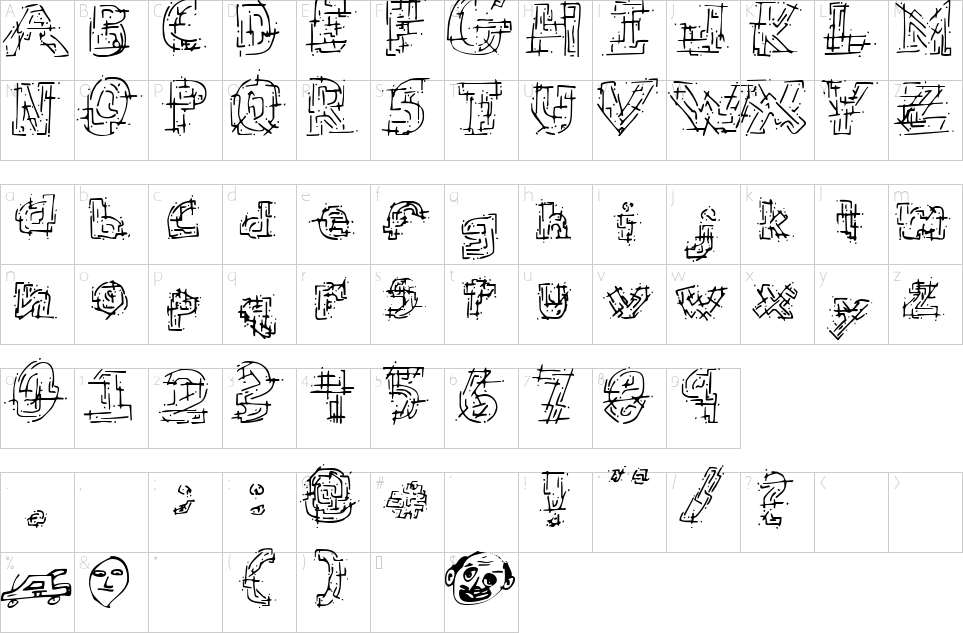
A fonte Chaotic Circuit é um adereço perfeito para quem busca algo que destaque seu design no meio vibrante e inovador do digital. Desenvolvida por Bionic Type, essa fonte criativa ganhou a confiança de muitos criadores ao longo de suas downloads. Com uma aparência que parece ser um circuito elétrico mal feito, mas cheia de vida, a Chaotic Circuit traz consigo um toque de energia e destruição que enriquece qualquer projeto. Seja para criar o próximo hit de design gráfico ou para dar vida ao seu próximo design de aplicativo, a Chaotic Circuit é uma escolha ótima para aqueles que buscam algo realmente único e invulgar, que se destaca da multidão. Com mais de 8. 284 downloads, a font Chaotic Circuit é um sucesso contínuo para designers e entusiastas de design que querem dar vida à seus projetos com uma escolha verdadeiramente inovadora.